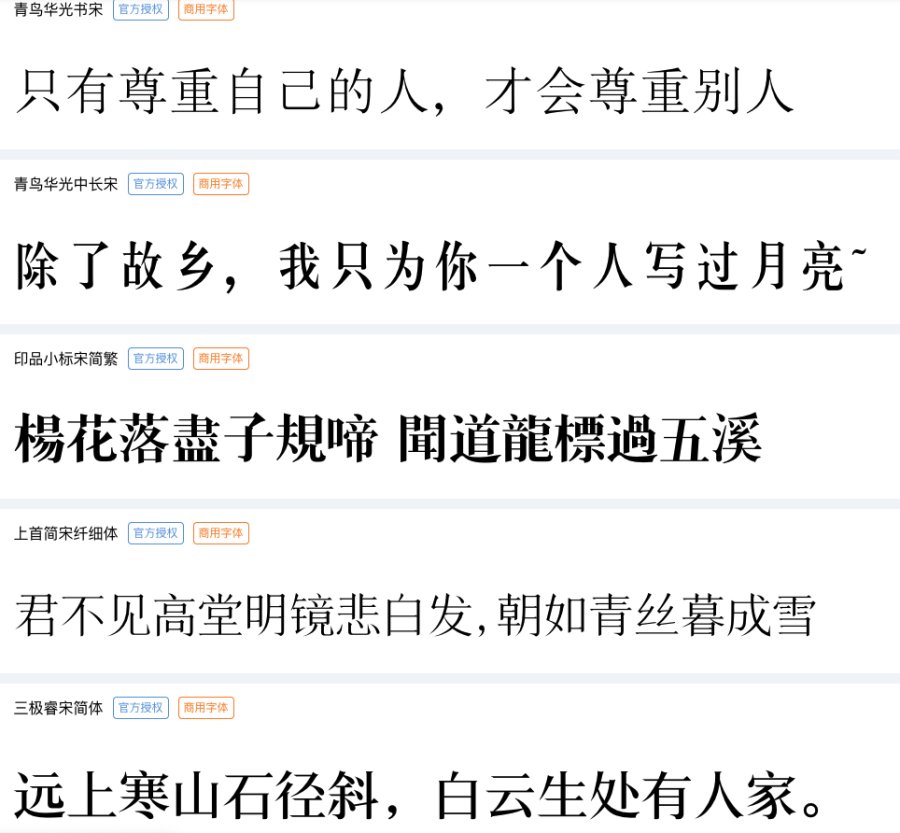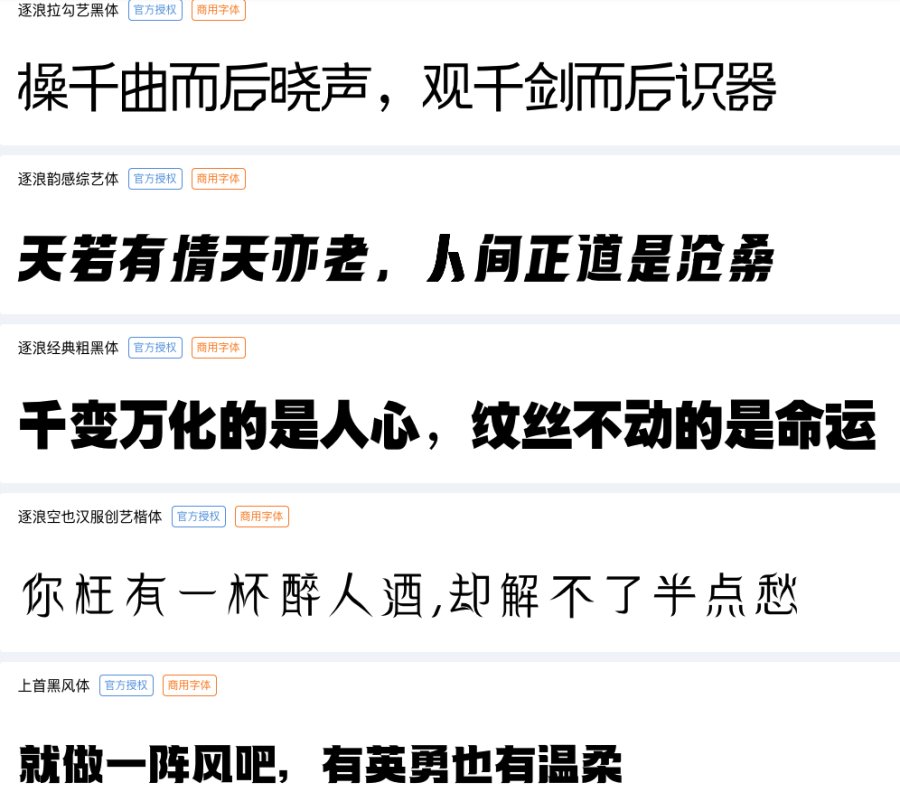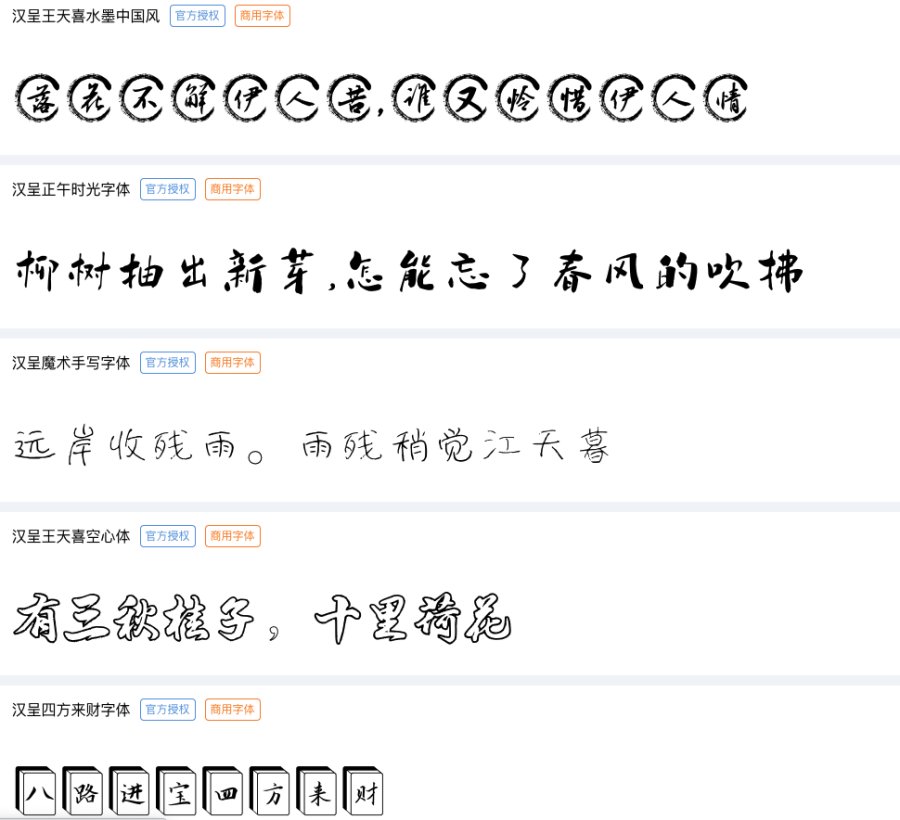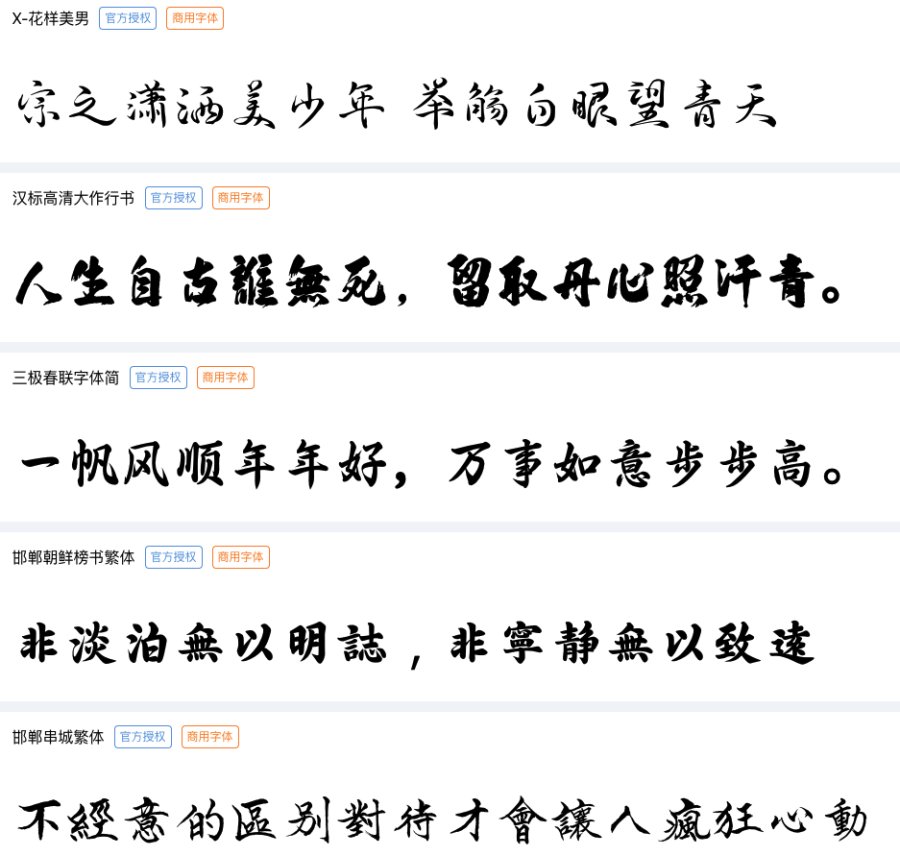
标题字应该要怎么选择呢?
标题字的字体和字号的正确选择对于准确传达主题内容和增强版面的效果有着不容忽视的作用。标题字的字体选择要依据主题内容,准确体现设计风格。
对于新闻类、科技类等版面的标题,可以选择宋体、黑体、综艺体等较严谨的字体;
宋体
黑体
对于娱乐类、休闲类等版面的标题,可以选择卡通体、美术体等活跃的字体;
对于历史类等版面的标题,可以选择书法体等体现传统的字体。
书法字体